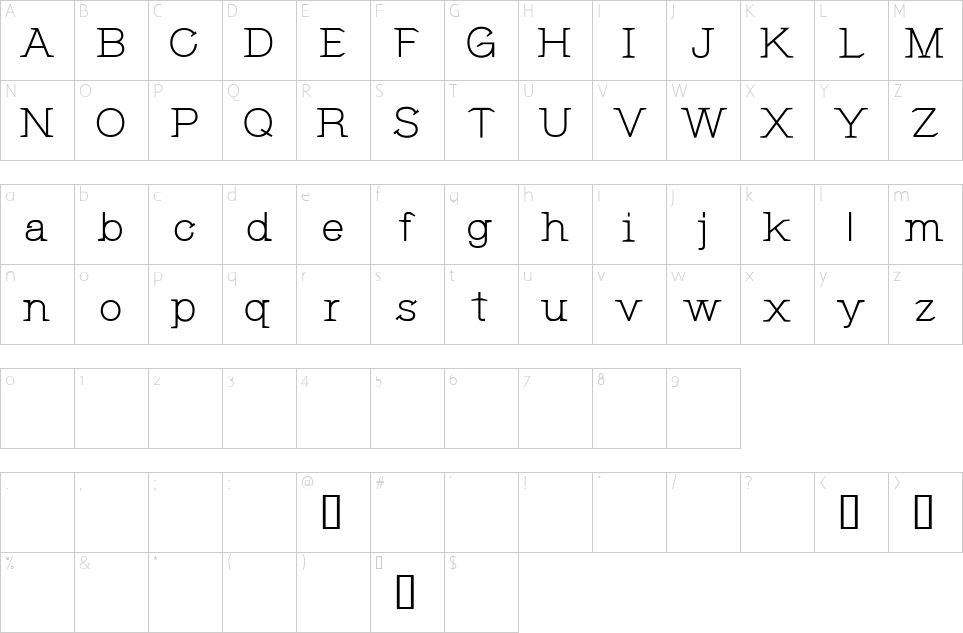
A fonte Jeanne Mance apresenta uma mistura sofisticada e elegante perfeita para designers que buscam um equilíbrio entre clareza legível e estética moderna. Desenhada pela CloutierFontes, a Jeanne Mance was projetada com base em influências do minimalismo contemporâneo, resultando num estilo suave e fluido que se adaptará bem a uma variedade de tipografias e texturas. Ela foi projetada para ser agradável tanto no uso padrão quanto em tamanhos mais grandes ou menores. Com sua versatilidade, é um excelente complemento para design gráfico, criação web, impressões digitais e até mesmo aplicação em interfaces de usuário onde exige um toque contemporâneo. Sua facilidade na utilização a torna perfeita para iniciantes e profissionais da arte gráfica que buscam uma fonte moderna e funcional. Com 2570 downloads, Jeanne Mance apresenta-se como uma opção de alta qualidade em nosso catálogo gratuito de fontes disponíveis para Windows e Mac.